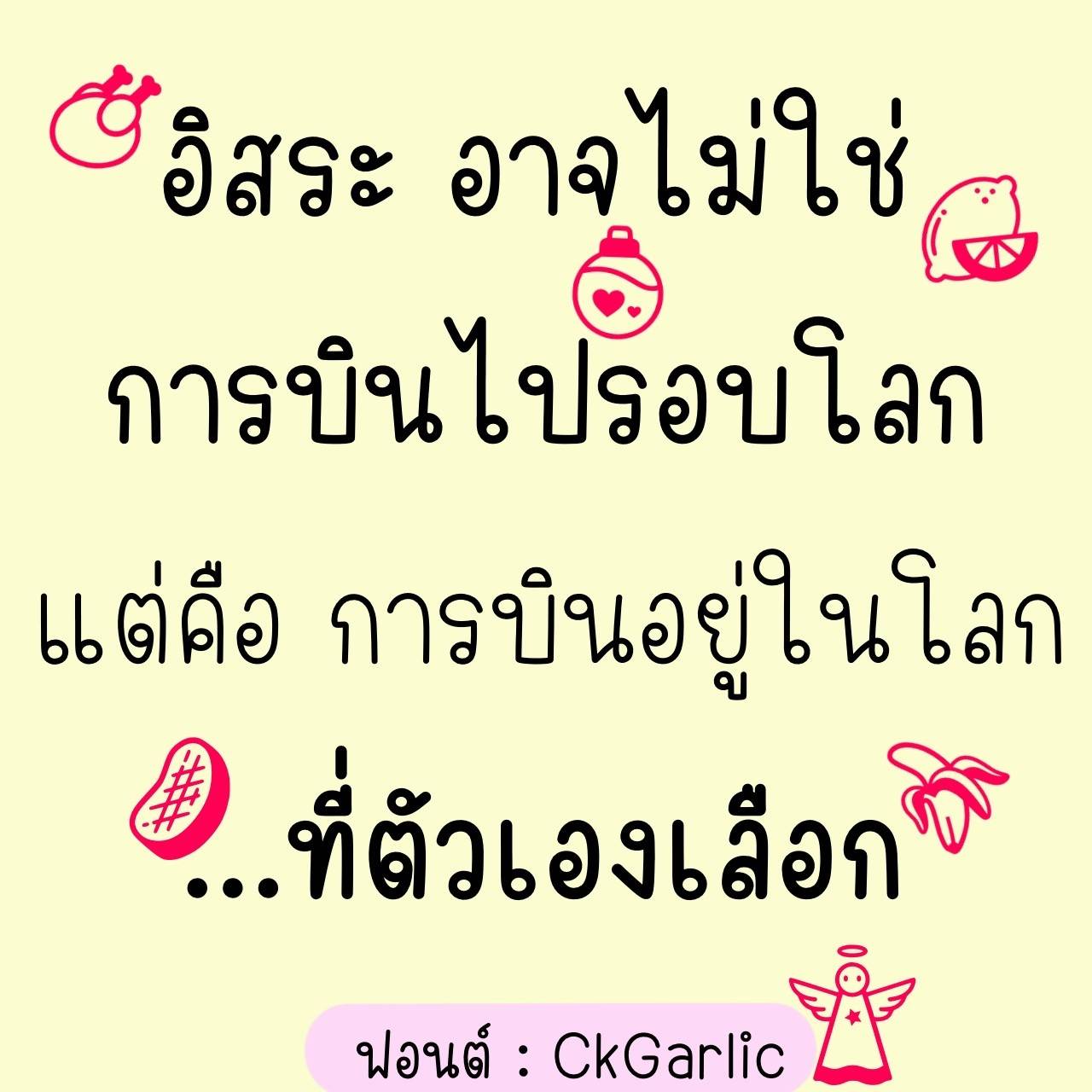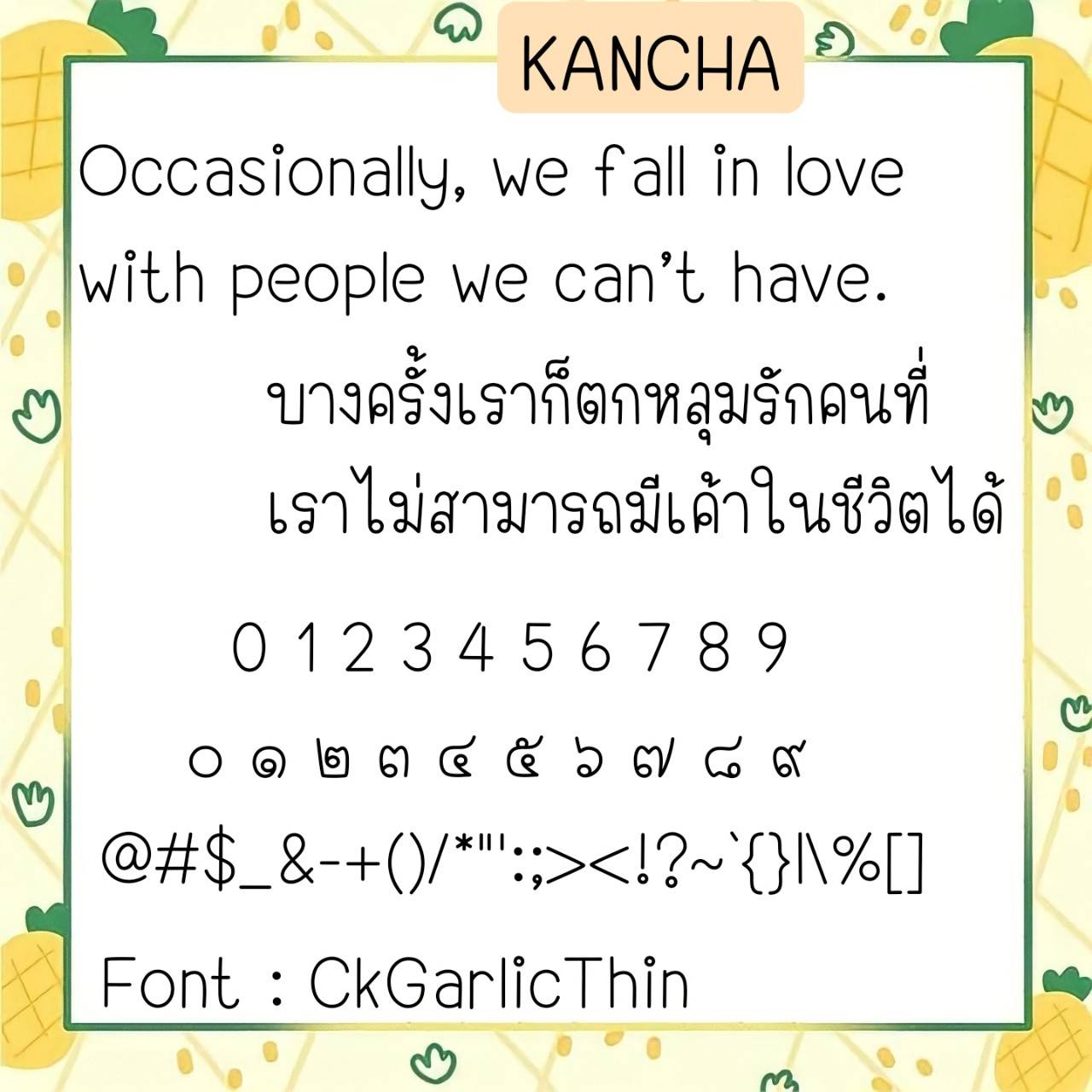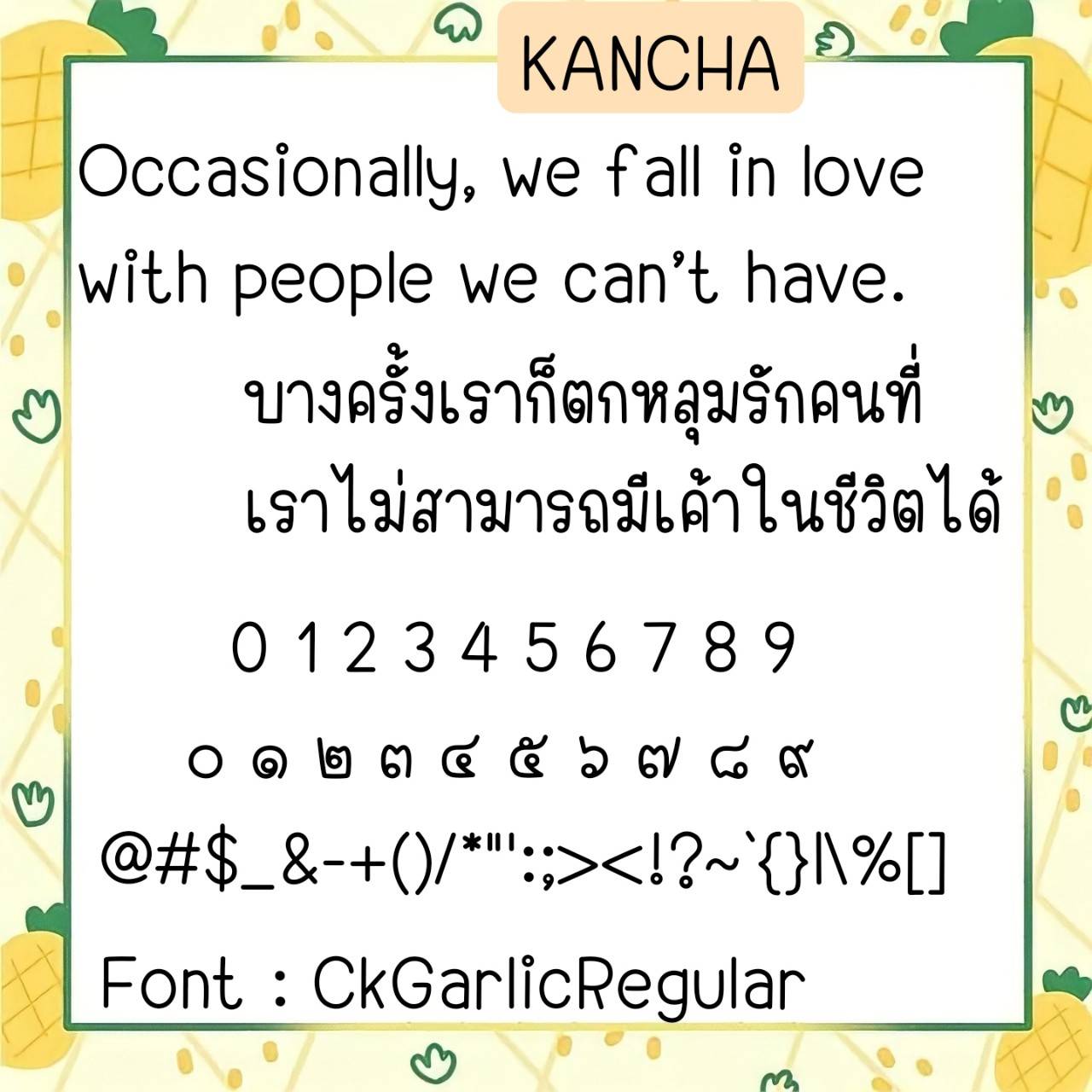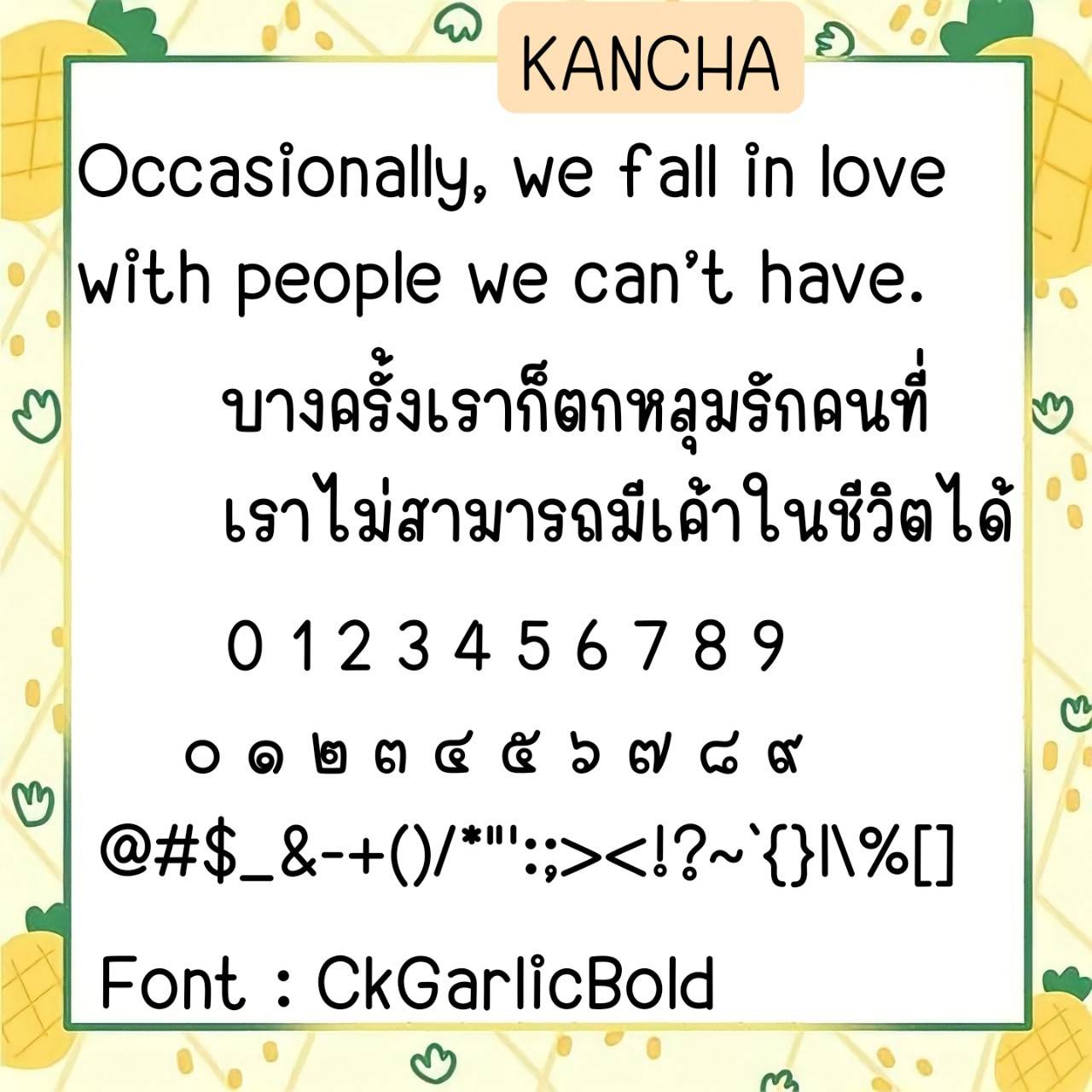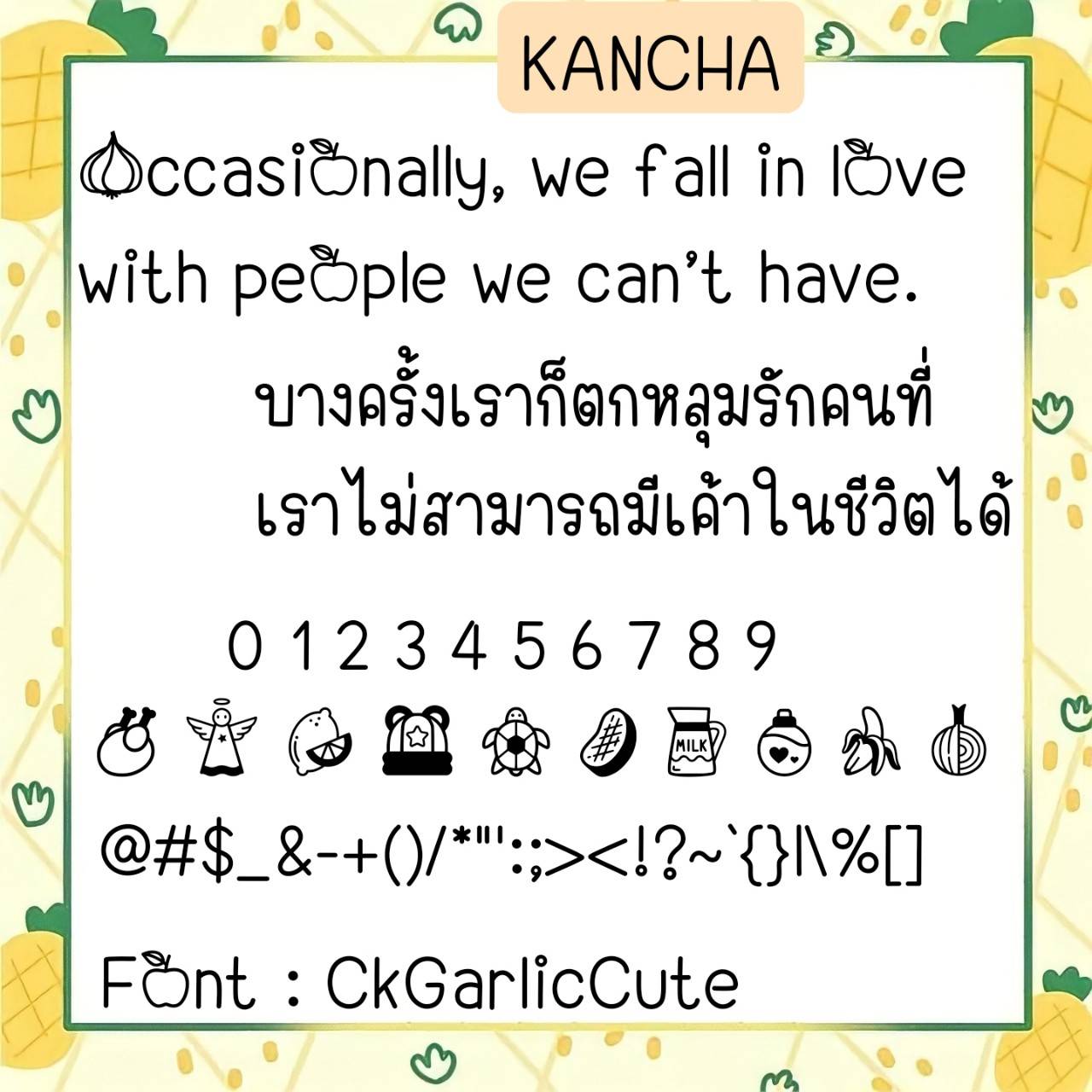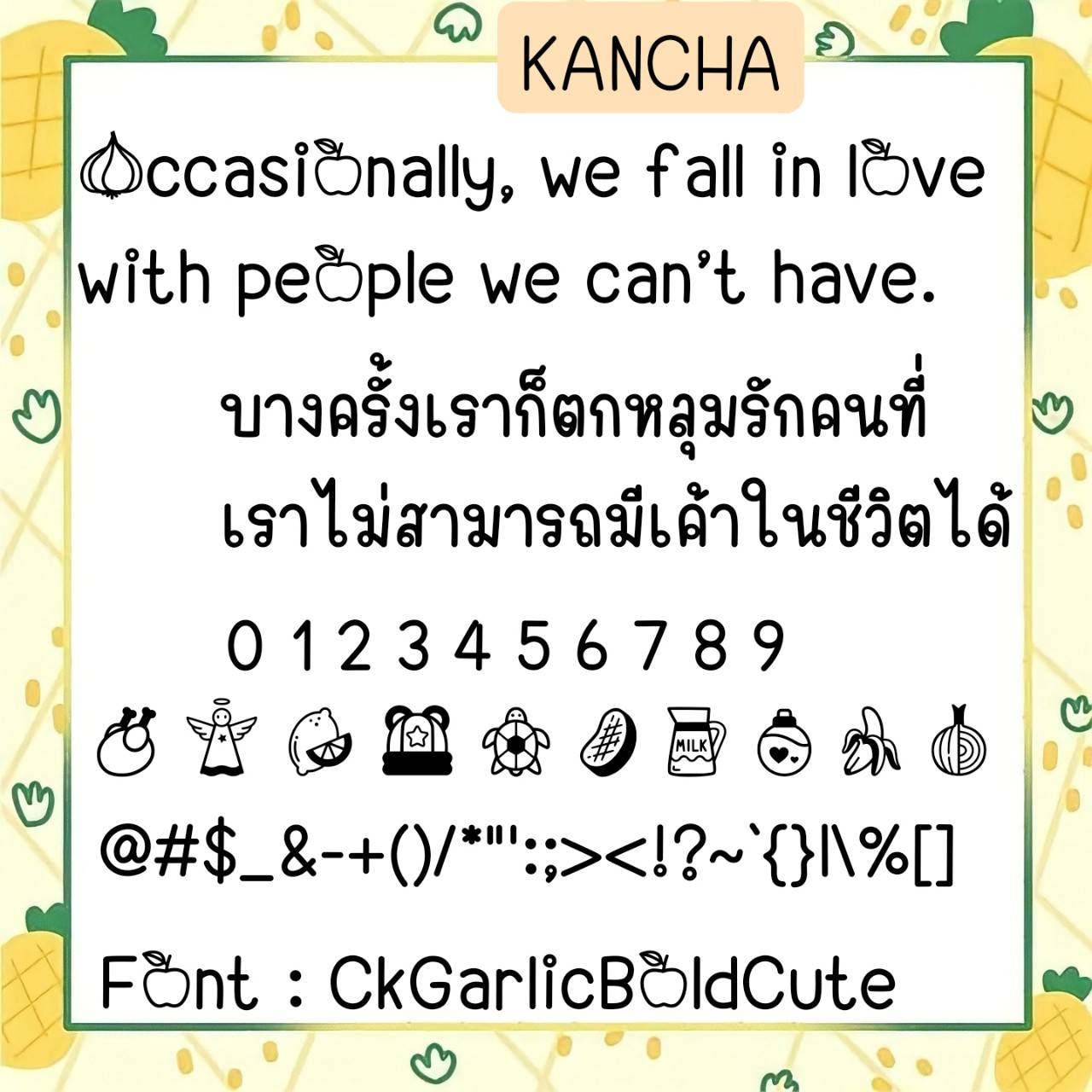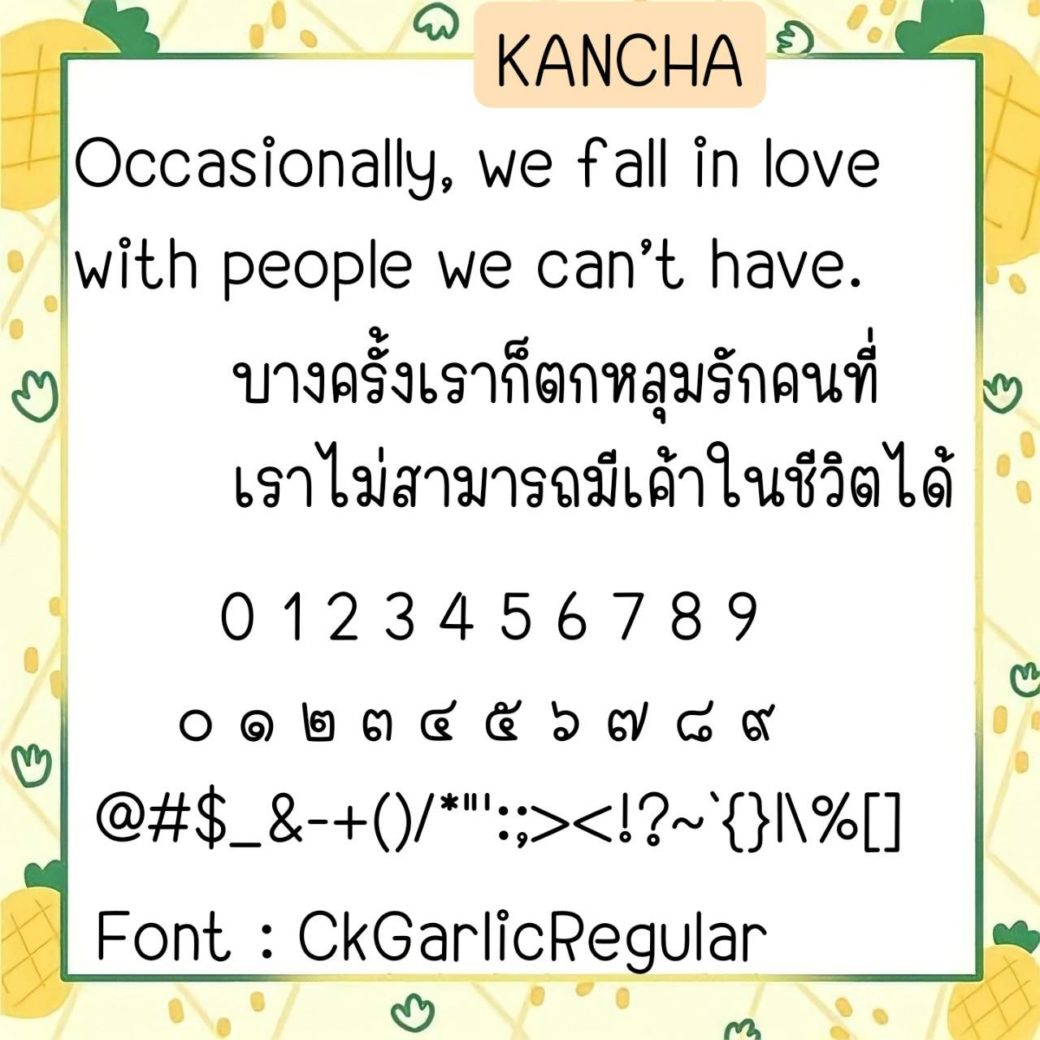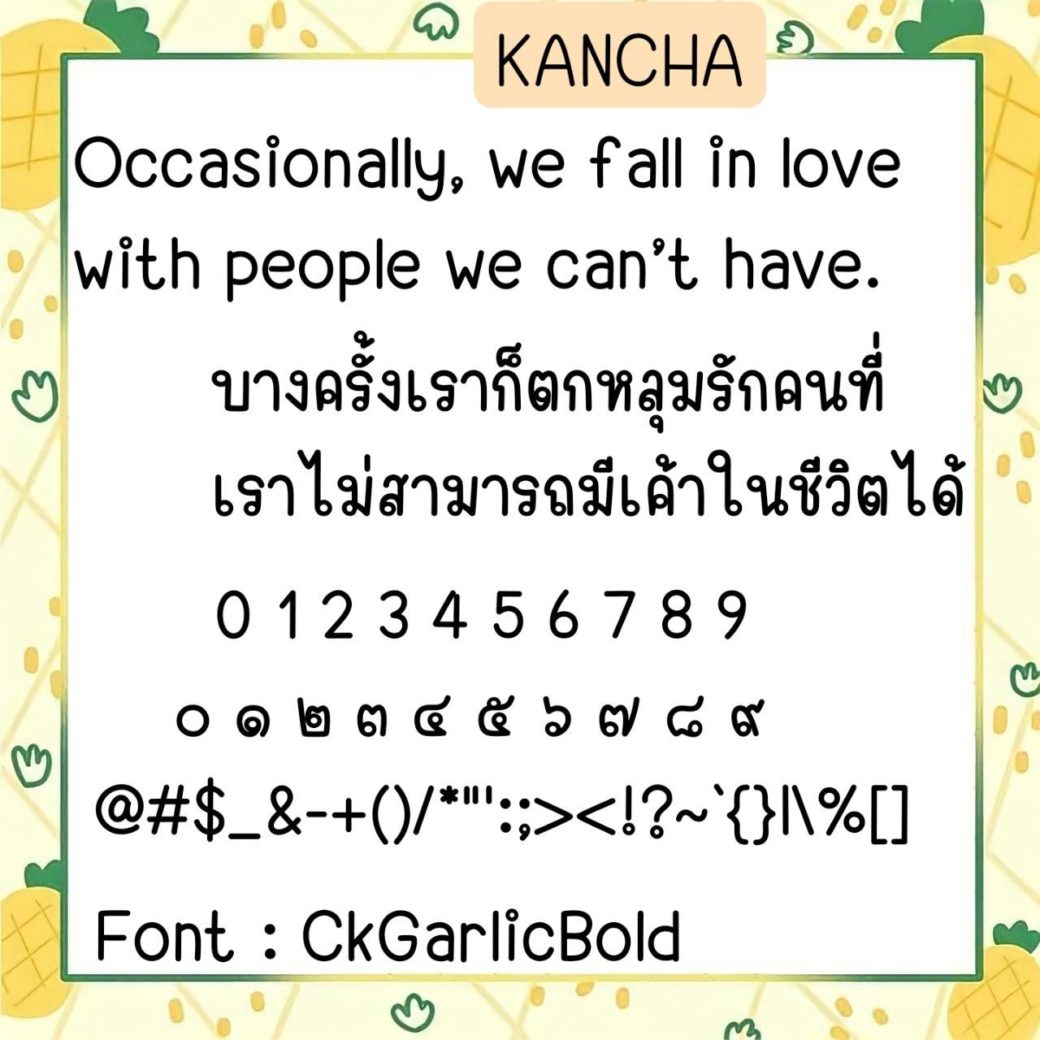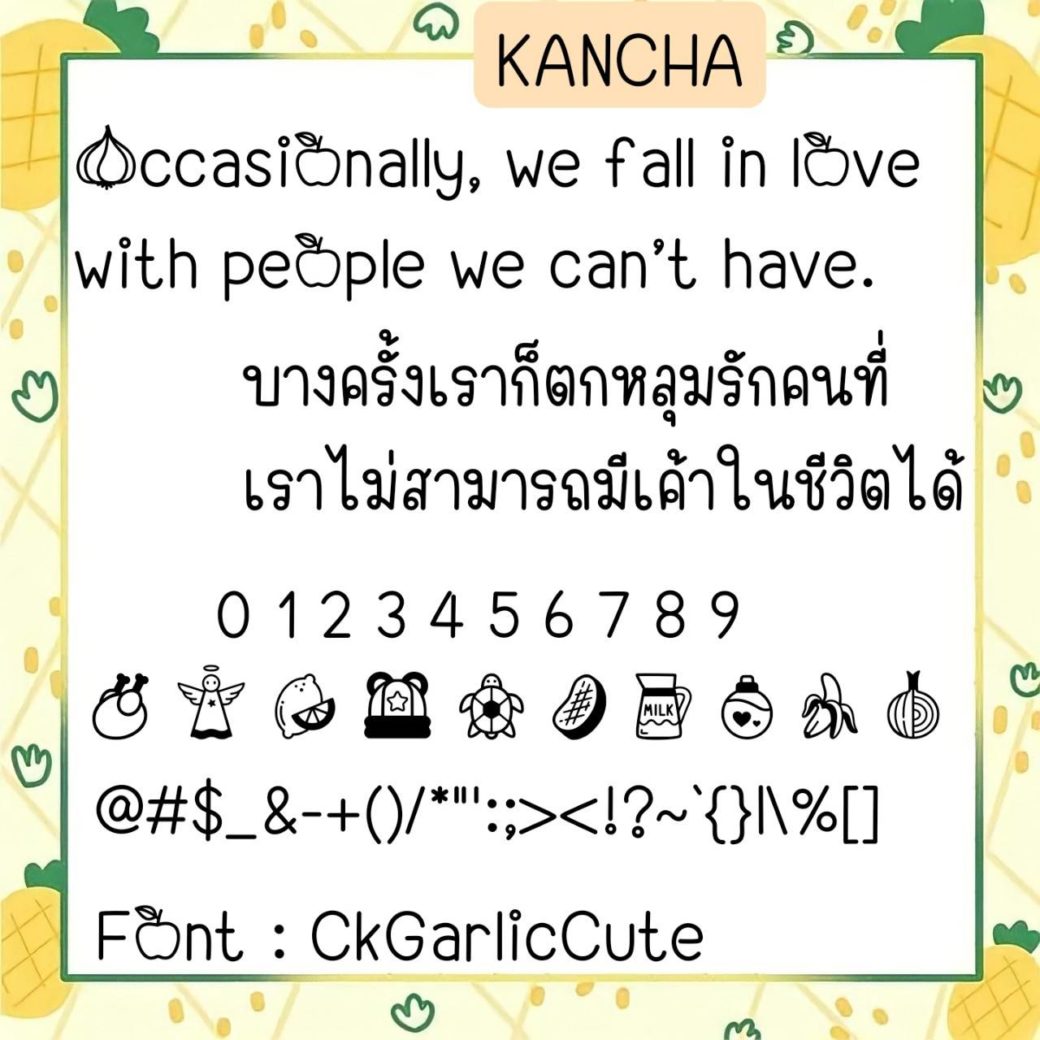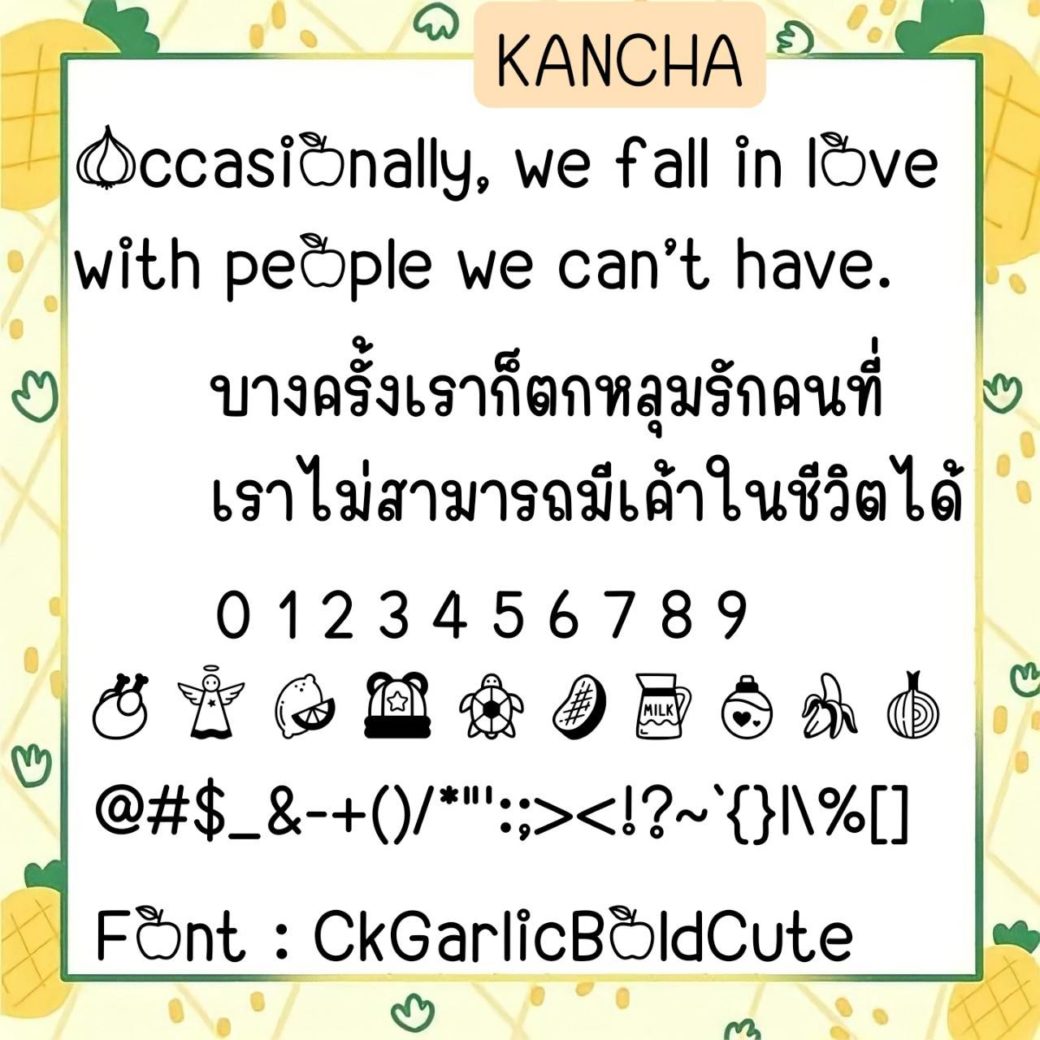
Font CkGarlic
ชื่อสินค้า : Font CkGarlic 💙
🔸ฟอนต์แนววัยรุ่น หัวมนๆรีๆ ขนาดตัวพอดีๆ เน้นความอ่านง่าย,ใช้งานได้หลากหลาย และยังมีไฟล์อิโมจิน่ารักๆแทนเลขไทยให้ในชุดด้วยค่ะ 🥰💙
🔹Teenage-style font, rounded head, good size, focusing on readability, can be used in a variety of ways. And there is also a cute emoji file instead of Thai numbers in the set as well. 🥰💙